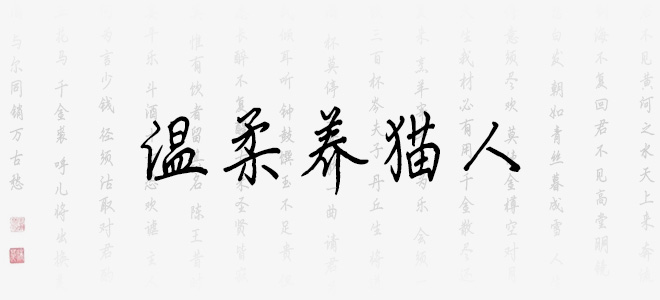
溫柔養(yǎng)貓人是麥拉風字庫推出的一款非常漂亮的手寫風格藝術(shù)字體,字體筆觸粗細適中,書寫端正,適合應(yīng)用于藝術(shù)設(shè)計、平面宣傳設(shè)計、網(wǎng)頁設(shè)計,書法字帖等領(lǐng)域,歡迎喜歡溫柔養(yǎng)貓人字體的朋友前來下載實用。
麥拉風溫柔養(yǎng)貓人